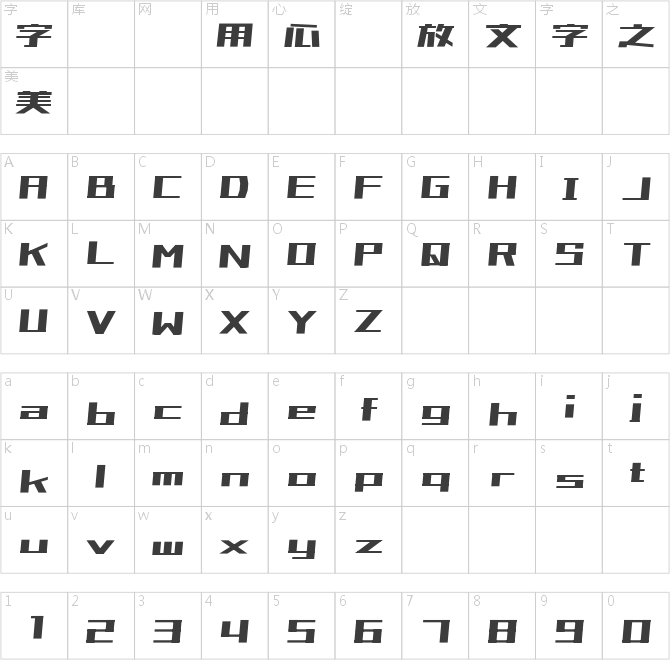
851ゴチカクット電機文 詳情頁
字體名稱: 851ゴチカク
字體類型: 日文字體
851ゴチカクット電機文
這是一款充滿銳利感的剛性字體,跟我們國內(nèi)的站酷高端黑的風格相類似,但是它有一定傾斜角度,看上去更有速度感。豎畫傾斜5°,目前收錄平假名、片假名、數(shù)字、JIS第1水準漢字+人名用漢字等。雖然文字還不夠多,但是現(xiàn)在作者還有繼續(xù)開發(fā)中